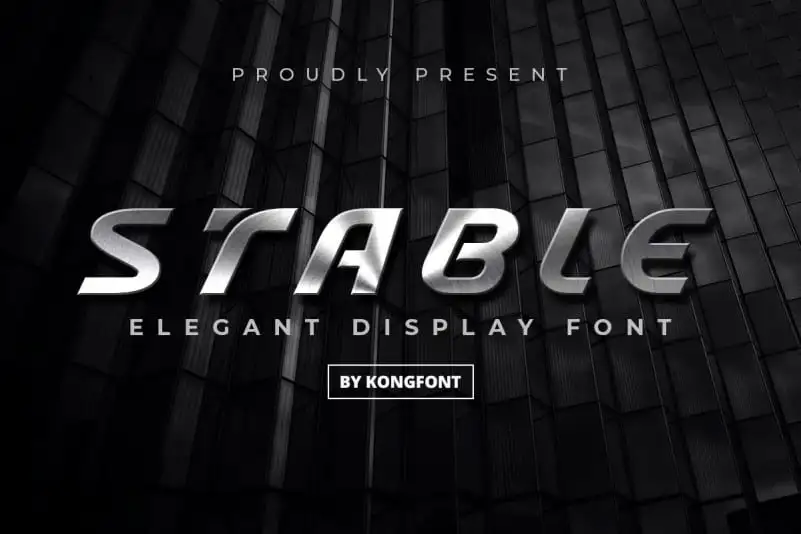
Stable Display Font – Download Grátis
A Stable Display Font é uma tipografia para displays que se destaca por sua estrutura limpa e a densidade alta dos caracteres. Inspirada no design moderno do século XX, essa fonte exibe letras maiúsculas e minúsculas idênticas. Ela é perfeita tanto para projetos de logotipo quanto para a identificação visual de marcas, logo, arte digital de letras, camisetas e roupas, panfletos, outdoors, publicações, anúncios, além de trabalhos que exigem uma marca única. Suas linhas retas e robustez em suas formas ajudam a transmitir confiança e simplicidade ao mesmo tempo. Seja para adicionar um toque moderno a sua próxima camisa ou criar uma identidade visual profissional para seu negócio, esta fonte é um excelente complemento.